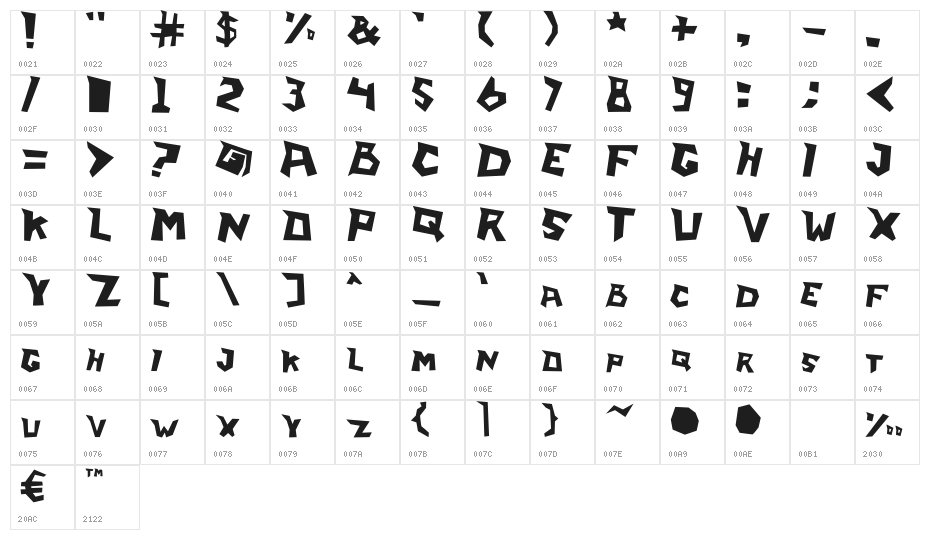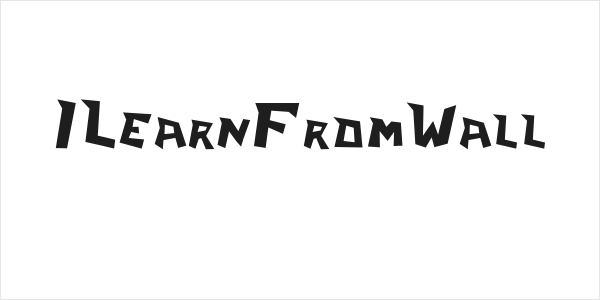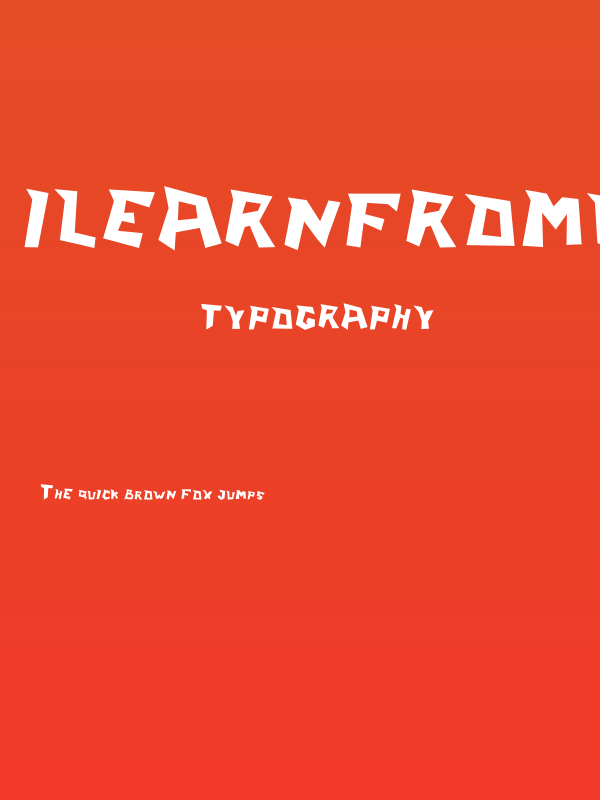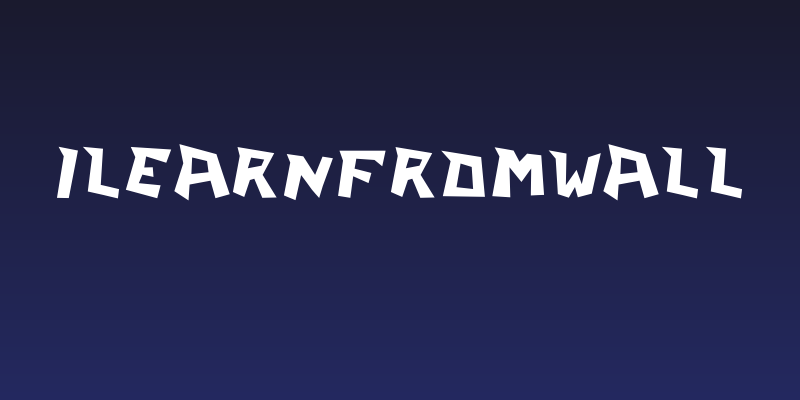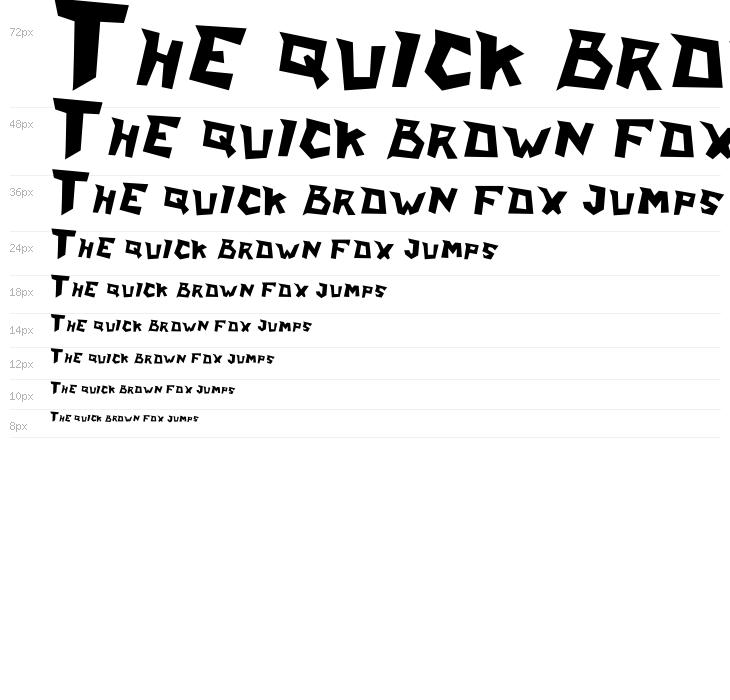
ILearnFromWall Font
| Stile generale | Modern, Urban, Edgy |
| Progetti proposti | Perfect for street art designs, music album covers, urban-themed posters, and edgy branding projects. |